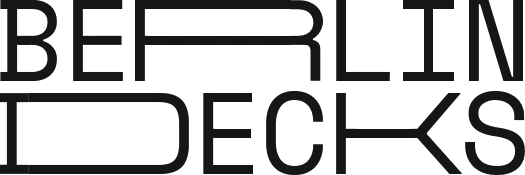
Schriften mit großen Unterschieden in der Breite der Versalien
(Schrift: Formula Condensed).
Interessant, dass hier beispielsweise C und G schmal sind obwohl sich die breitere Form wie bei O oder Q anbieten würde. Schräge Mischung …
Sowohl das weite W im Kleingedruckten wie auch der Wortaut des Kleingedruckten lassen mich vermuten, dass da nicht für jeden Buchstaben ein Beispiel gewählt wurde … ich hatte jetzt aber auch kleine Lust, die probeweise herunterzuladen, um das zu zu überprüfen.
Interessant, dass hier beispielsweise C und G schmal sind obwohl sich die breitere Form wie bei O oder Q anbieten würde. Schräge Mischung …
Das Font-in-use-Beispiel zeigt, dass es auch für C und G breite Alternativformen gibt. Die Grafik oben ist dahingehend missverständlich …
Die Grafik oben ist dahingehend missverständlich …
In der Unterzeile der Grafik steht, dass es für alle Versalien und Ziffern breite Alternativen gibt. Hatte ich in dieser Größe schlicht überlesen ... Sorry!
Haha ... das unterstützt die These, dass breitlaufende Schriften in beispielsweise 6 Punkt oft besser Lesbar sind als schmallaufende Schriften in 8 Punkt.
Bei der Space Mono (Berlin Decks, Colophon) stören mich nur die rar und inkonsequent verteilten Slabserifen (siehe B, D) – dann hätte man es auch bleiben lassen können. 🤷🏼‍♂️
Interessant, dass beide Erscheinungsbilder neben der Schrift auch das gleiche Farbkonzept verwenden. Wenn man auf beiden Seiten das Logo eliminiert, bleibt nicht mehr viel übrig, um beide Brandings auf den ersten Blick klar voneinander zu trennen. :shock: